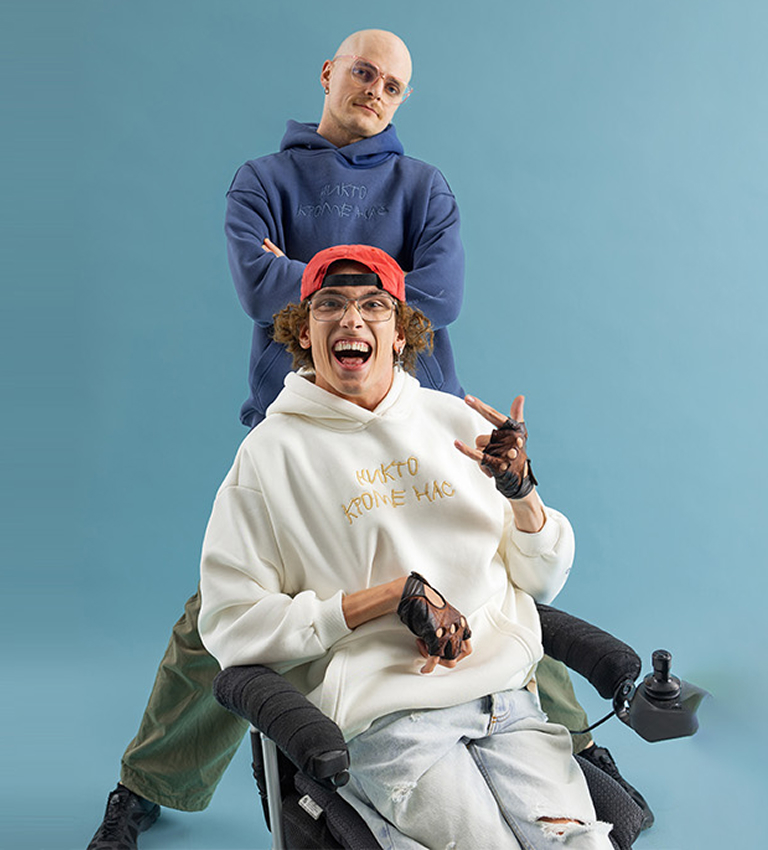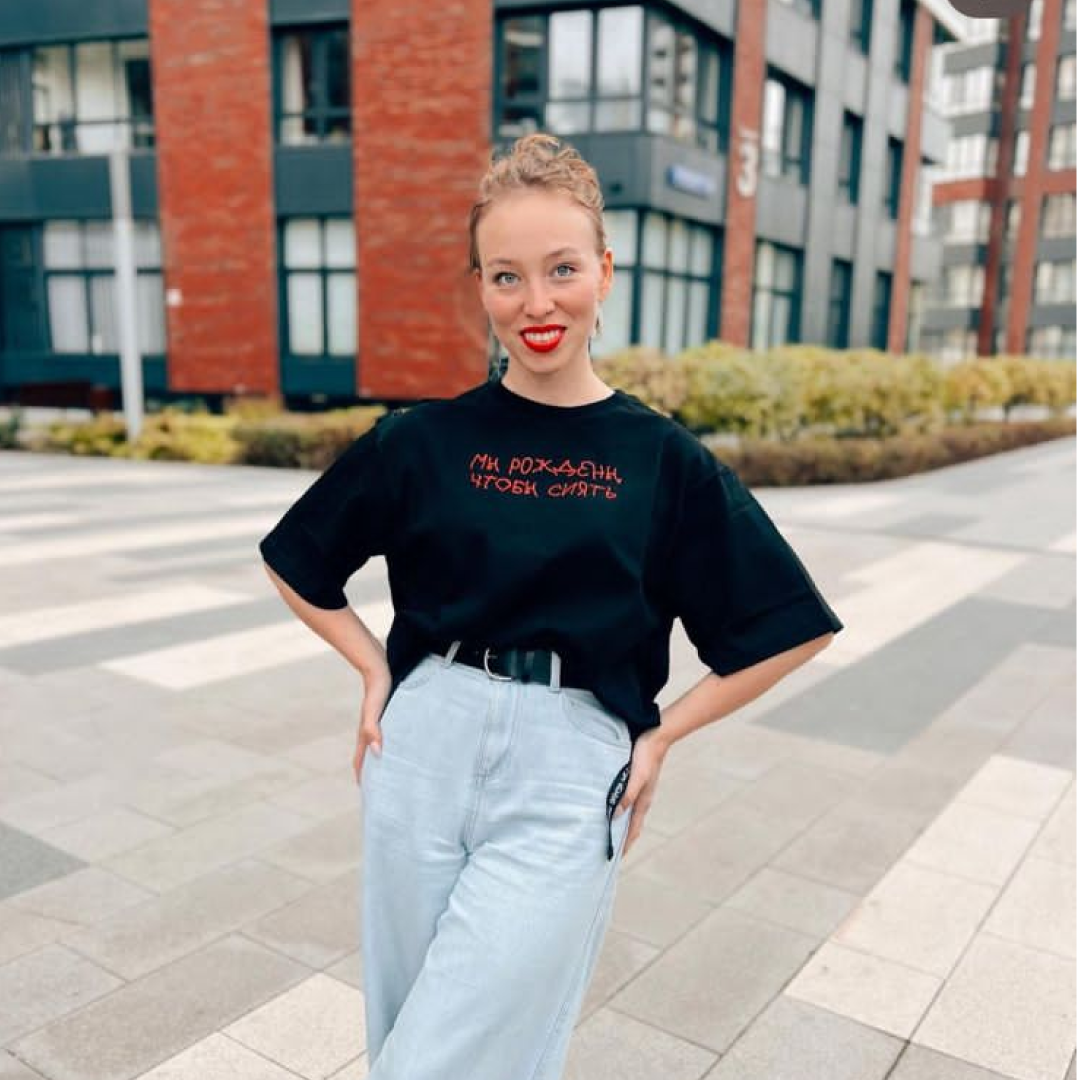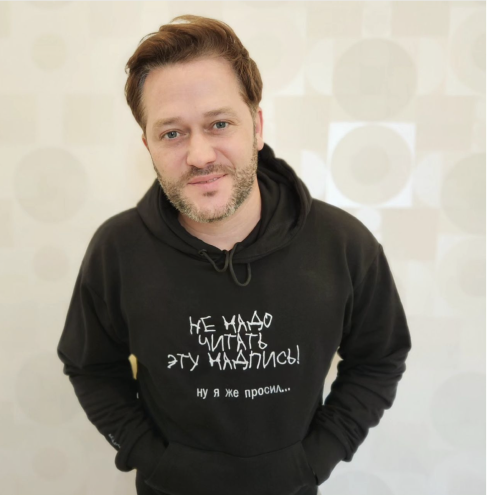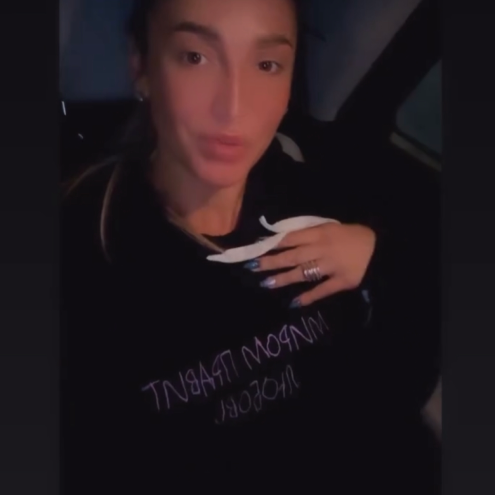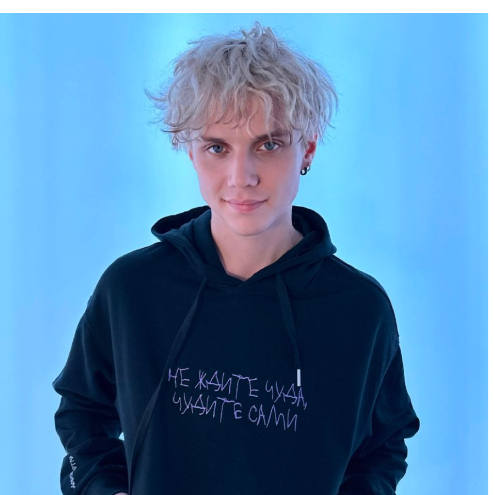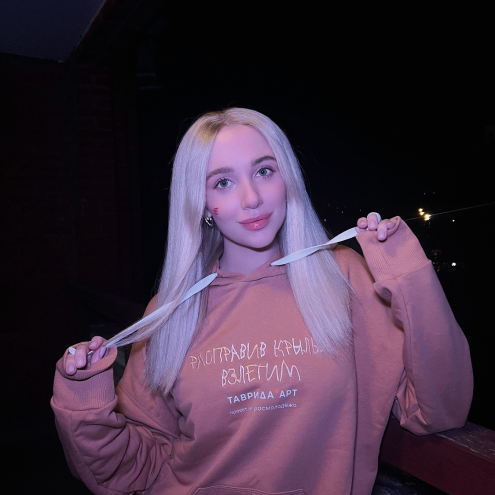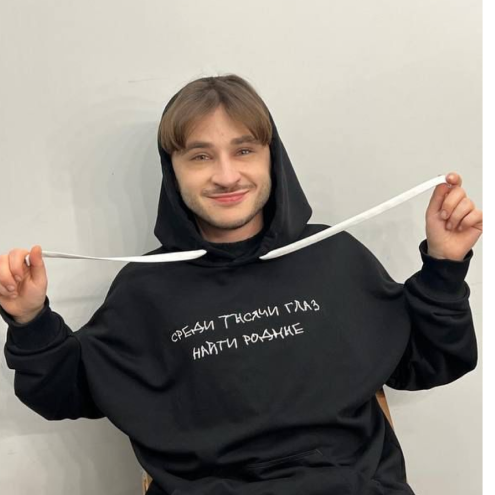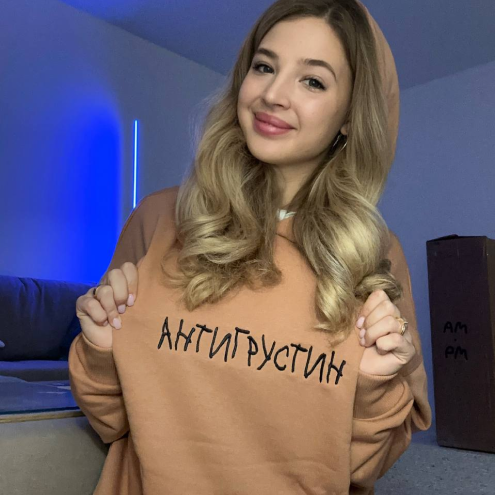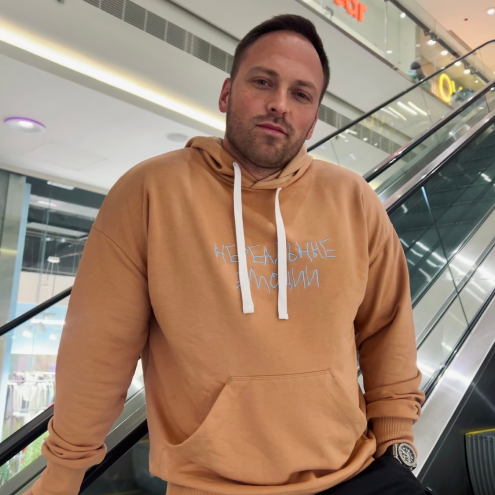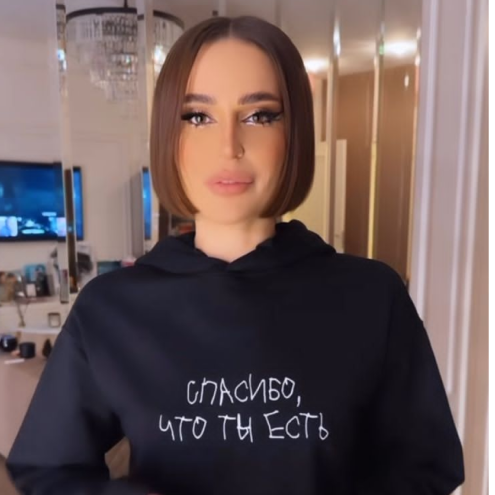
Что такое Доброшрифт?
Дети с ДЦП создали специальные прописи, а дизайнеры собрали из них шрифт, который полностью состоит из этих особенных букв.
Теперь сотни компаний и тысячи людей используют Доброшрифт каждую первую среду октября, чтобы привлечь внимание к проблемам маломобильных людей и оказать помощь тем, кто в ней нуждается.